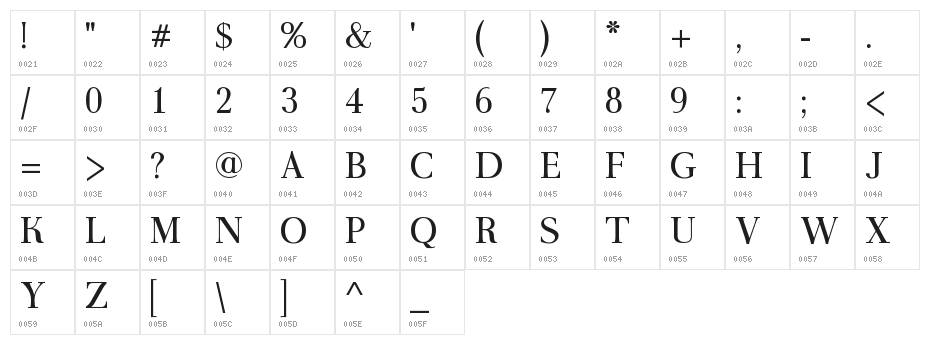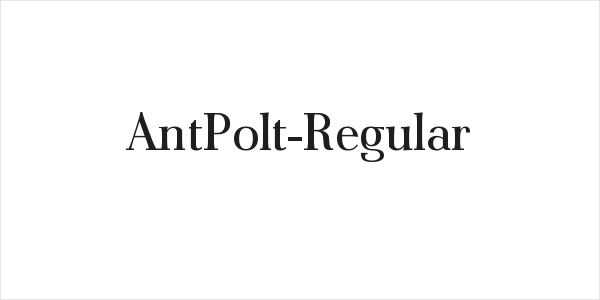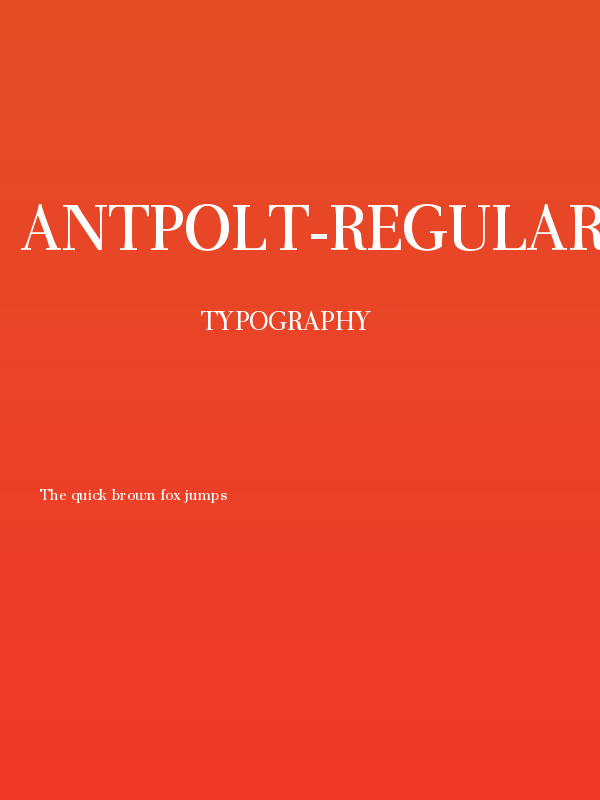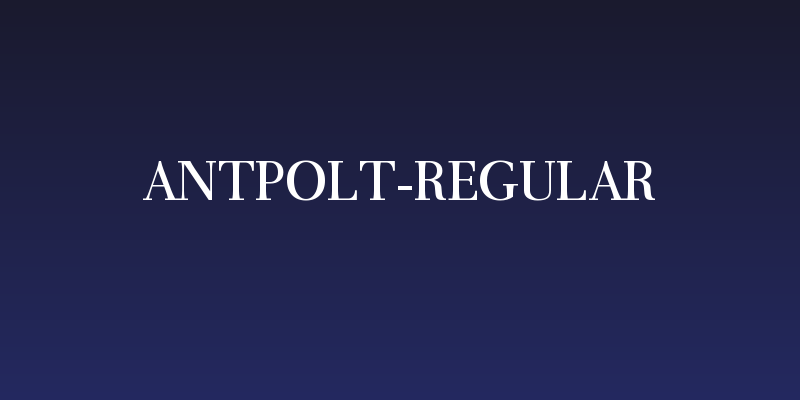
AntPolt-Regular Font
✎ Serif
| 分类 | Serif |
| 整体风格 | Classic |
| 使用场景 | Headlines, Body text, Logos |
| 推荐项目 | Ideal for editorial design, book covers, formal invitations, and branding materials that require a touch of elegance and tradition. |